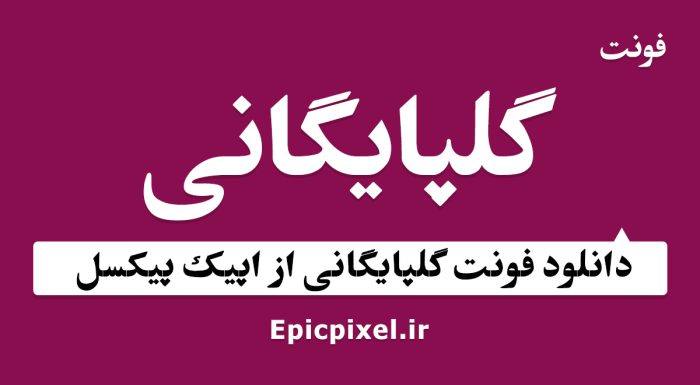
فونت گلپایگانی، با الهام از آثار بهزاد گلپایگانی، از پیشگامان تایپوگرافی مدرن ایران، طراحی شده و اصالت و زیبایی خاصی به متن های شما می بخشد. این فونت، با حفظ اصالت حروف فارسی، ظاهری مدرن و پویا به نوشته ها می دهد و برای استفاده در عناوین، متون کوتاه، مجلات و مطبوعات بسیار مناسب است.
ویژگی برجسته ی این فونت، حفظ تعادل بین سنت و مدرنیته است؛ به گونه ای که در عین پایبندی به ساختار کلاسیک حروف فارسی، حسی نو و تازه را القا می کند. این ویژگی باعث می شود متن های شما همزمان هم اصیل به نظر برسند و هم جذاب و چشم نواز.
اگر به دنبال فونتی هستید که به نوشته هایتان هویتی خاص ببخشد و در عین حال خوانایی بالایی داشته باشد، فونت گلپایگانی انتخابی ایده آل است. این فونت با طراحی منحصر به فرد خود، به متن های شما جلوه ای ویژه می بخشد و آنها را از سایر نوشته ها متمایز می کند. استفاده از این فونت در طراحی های گرافیکی، به ویژه جلد کتاب، پوستر و مجله، می تواند تأثیر بصری فوق العاده ای داشته باشد.
دوست عزیز، فونت گلپایگانی منتسب به گرافیست فقید استاد بهزاد گلپایگانی است.
فونت گلپایگانی ربطی به دستخط آیت الله العظمی گلپایگانی داره؟؟؟